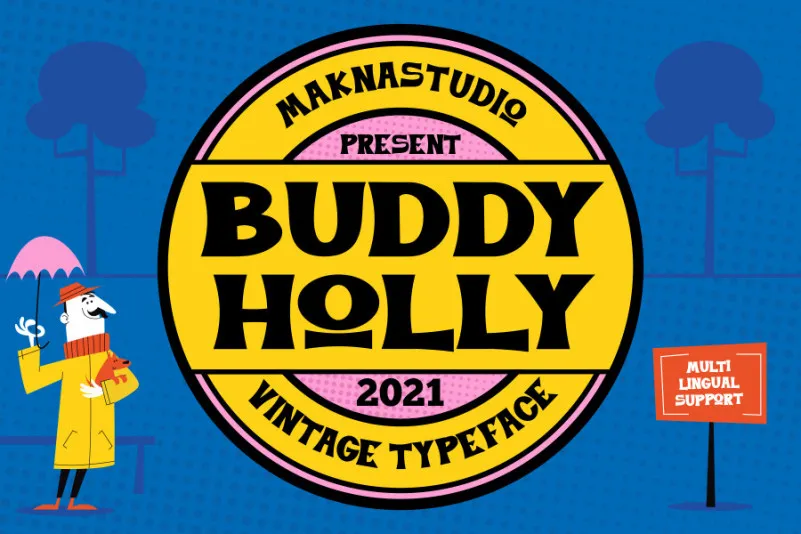
Buddy Holly Display Font – Download Grátis
Esta é uma fonte serif vintage criada pela MaknaStudio para projetos que valorizam temas antigos e linhas retrô. O estilo Buddy Holly Display Font é perfeito para incorporar elementos nostálgicos de maneira elegante e sofisticada ao seu design. Suas linhas curvas e detalhes delicados se sobressaem, proporcionando uma sensação única que combina charme antigo com modernidade contínua. Ideal para gráficos digitais, como logotipos, títulos de páginas ou anúncios em revistas vintage, Buddy Holly Display é a escolha perfeita para quem deseja manter o toque único e autêntico de um design clássico no seu trabalho.